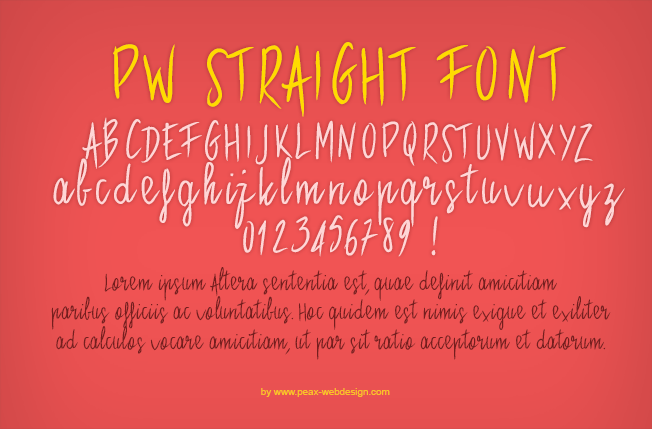
Une nouvelle typo pour ce mois de juillet : PW Straight. Elle a l'aspect d'une écriture au pinceau, avec ses pointes effilées, et se prête à tout type d'utilisation, aussi bien moderne que rétro.